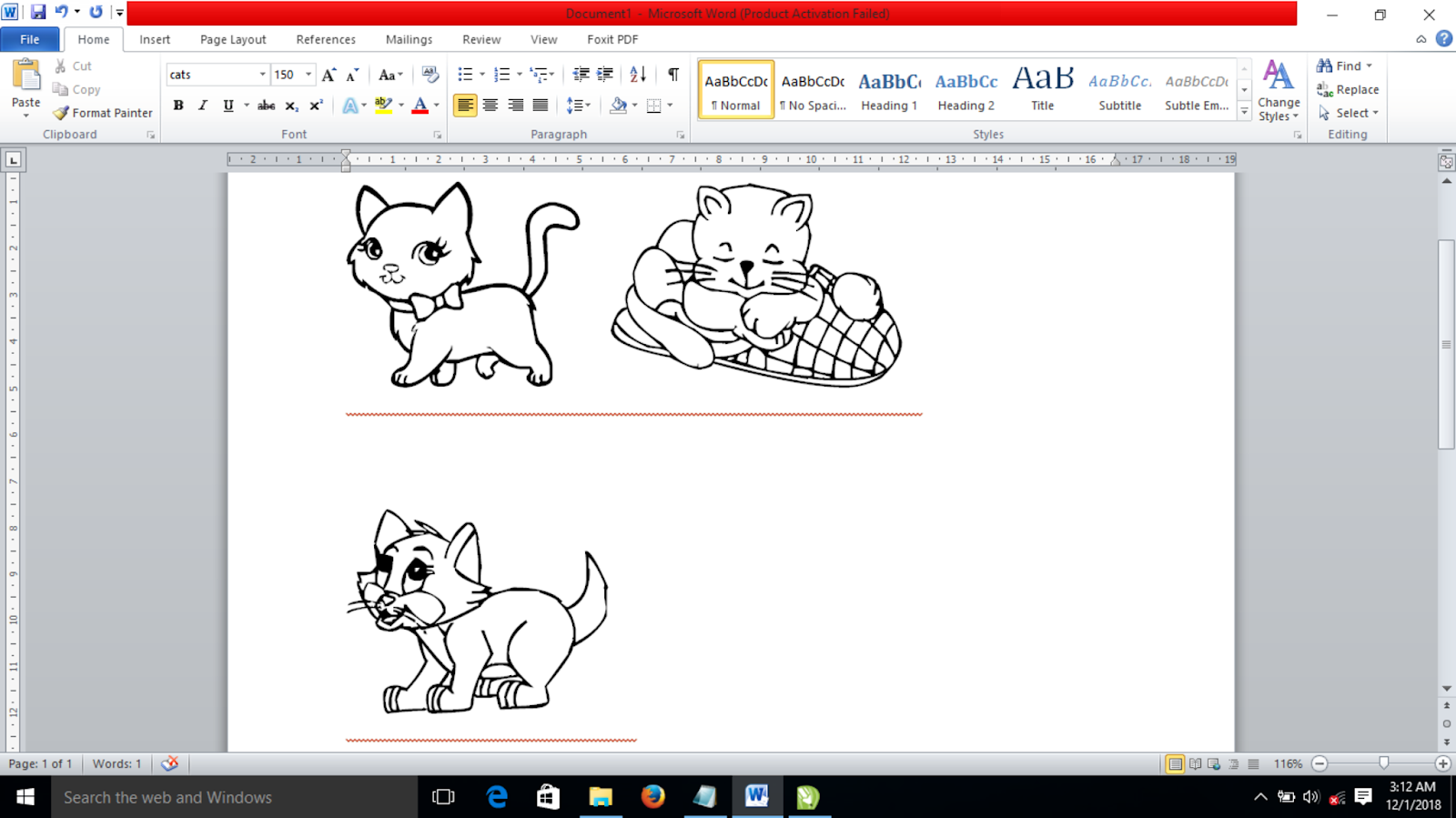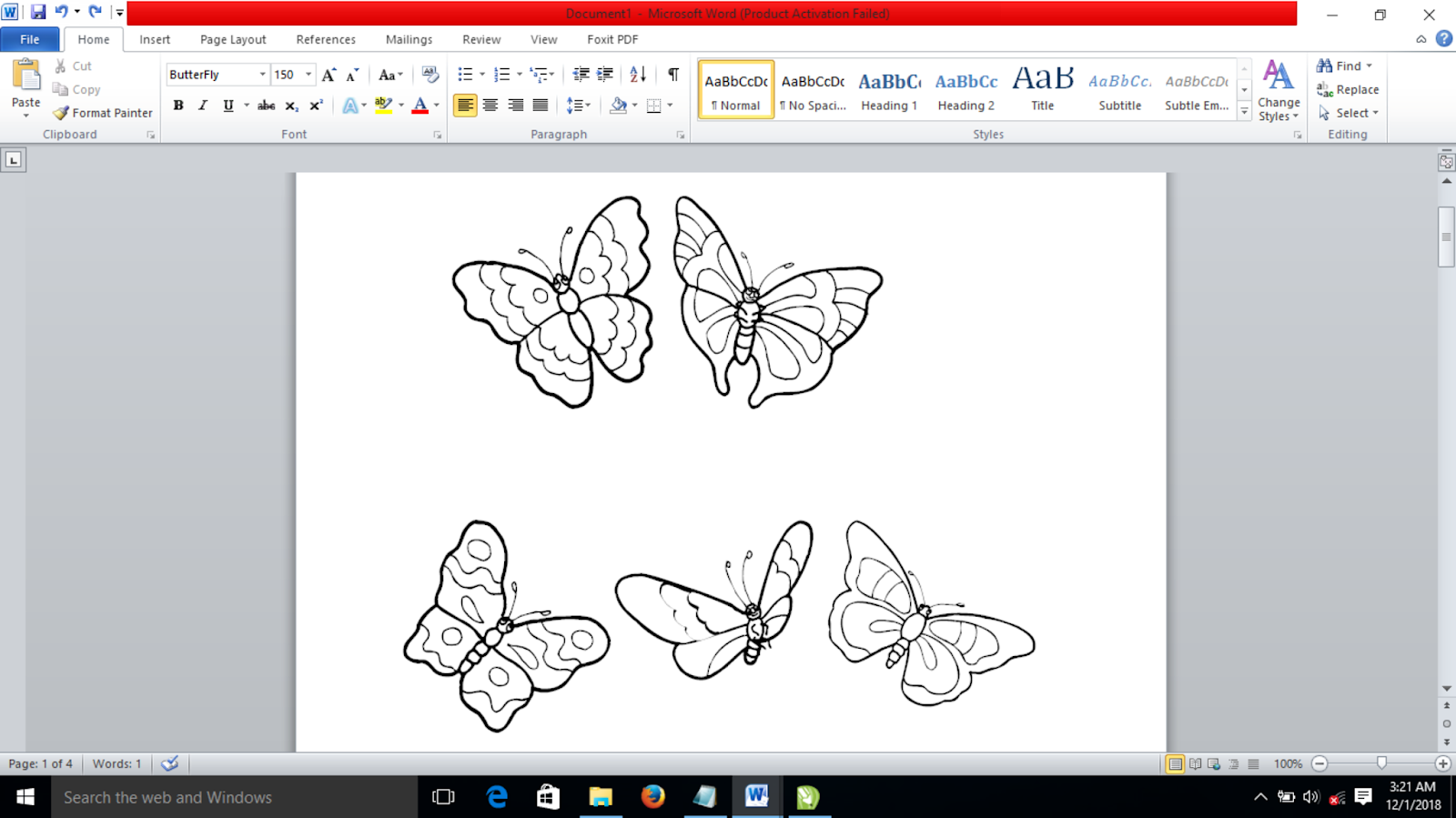
Sahabat mempunyai anak yang gemar mewarnai ? dan sahabat ingin membuatkannya lembar kerja mewarnai sendiri ? Tapi, sahabat tidak bisa menggambar ?. Jangan khawatir, berikut kami memberikan referensi font bentuk binatang yang bisa sahabat gunakan sebagai bahan untuk membuat lembar kerja mewarnai. Cara menggunakannya sama dengan font-font pada umumnya ya dan jangan lupa Caps Locknya dinyalakan.